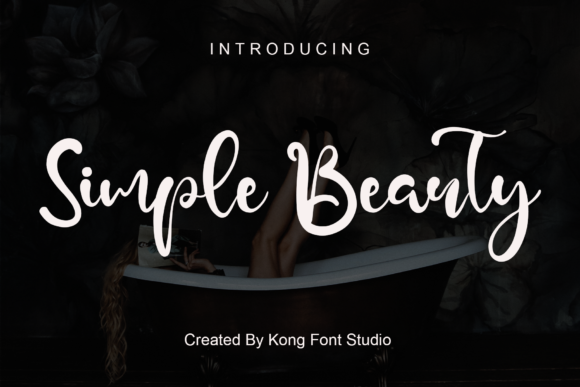
Simple Beauty
Jika anda sedang mencari aset berkualiti tinggi seperti Simple Beauty, pakej premium ini merupakan pilihan yang hebat untuk projek kreatif anda.
Sama ada anda mencipta produk POD (Print on Demand), jemputan perkahwinan atau grafik media sosial, Simple Beauty amat bersesuaian.